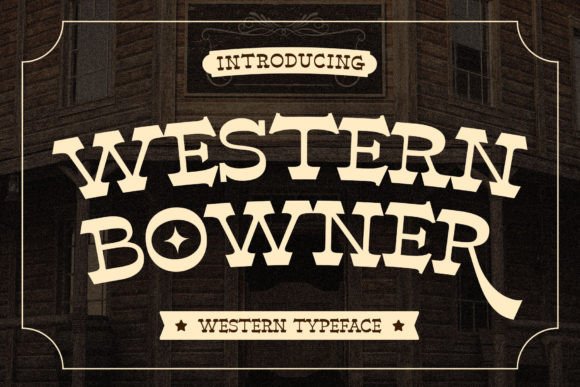
Western Bowner
Western Bownerのような高品質の素材をお探しの場合、このプレミアムパッケージはクリエイティブなプロジェクトに素晴らしい選択です。
POD(オンデマンド印刷)製品、結婚式の招待状、またはソーシャルメディアのグラフィックを作成している場合でも、Western Bownerは理想的です。